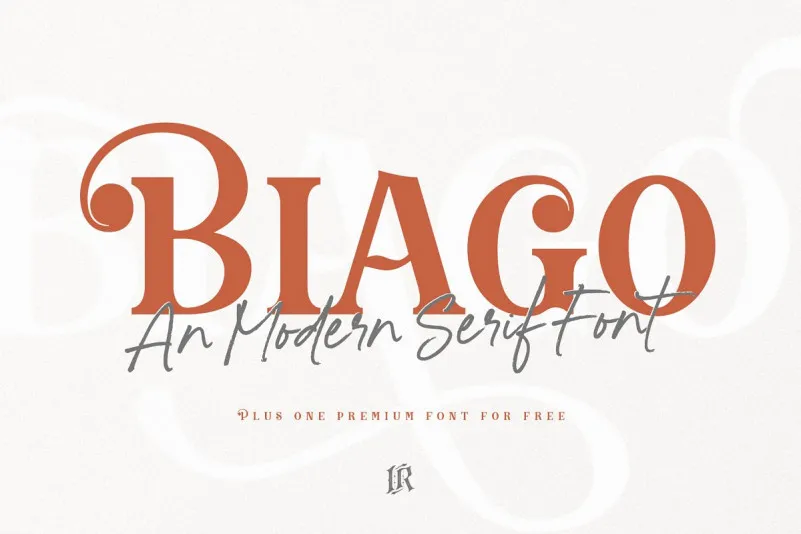
Biago Font Duo é uma elegante combinação entre serif e escrita à mão, ideal para tornar seus projetos mais sofisticados. Desenvolvida por Ivan Rosenberg, esta fonte oferece alternativas estilizadas que criam muitas variações práticas. Além disso, você recebe The Brightside, uma outra font premium com a qual Biago Serif faz um ótimo par – grátis para download. Perfecta para aplicar em website headings, cartazes, postais de restaurante, revistas e muito mais. Tente usá-la em seu próprio negócio, certamente vai dar um toque especial ao design.